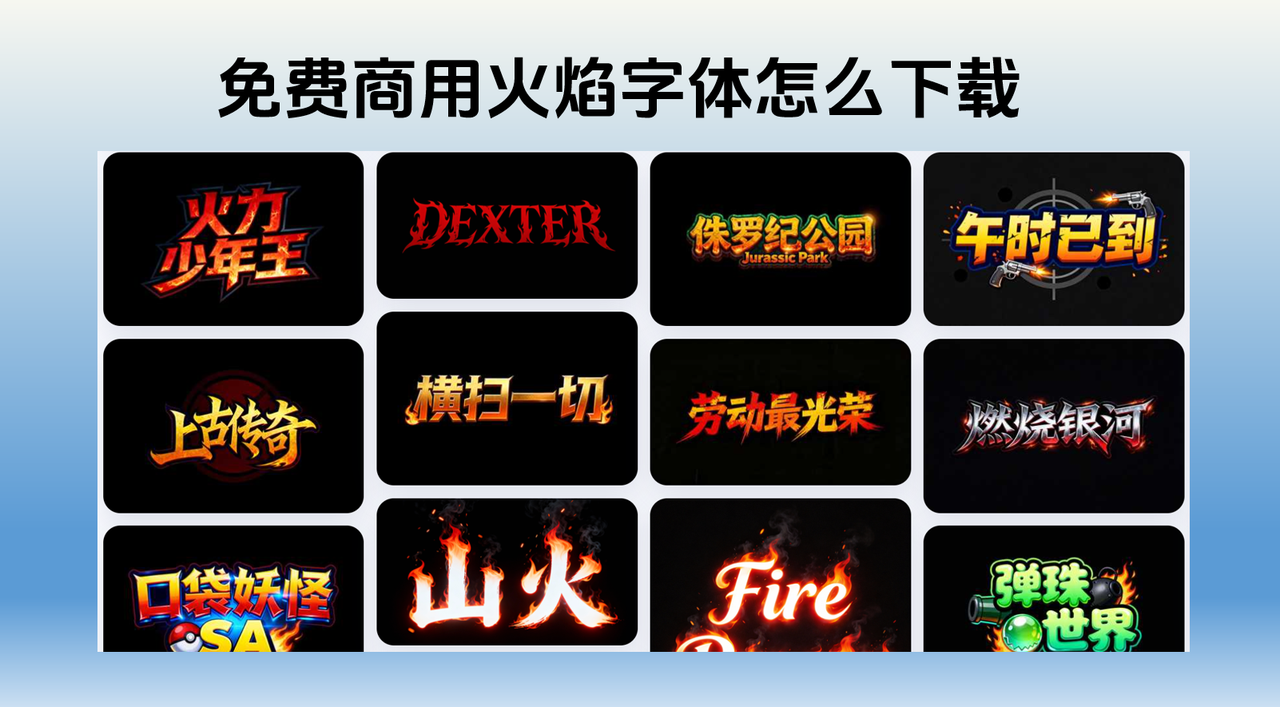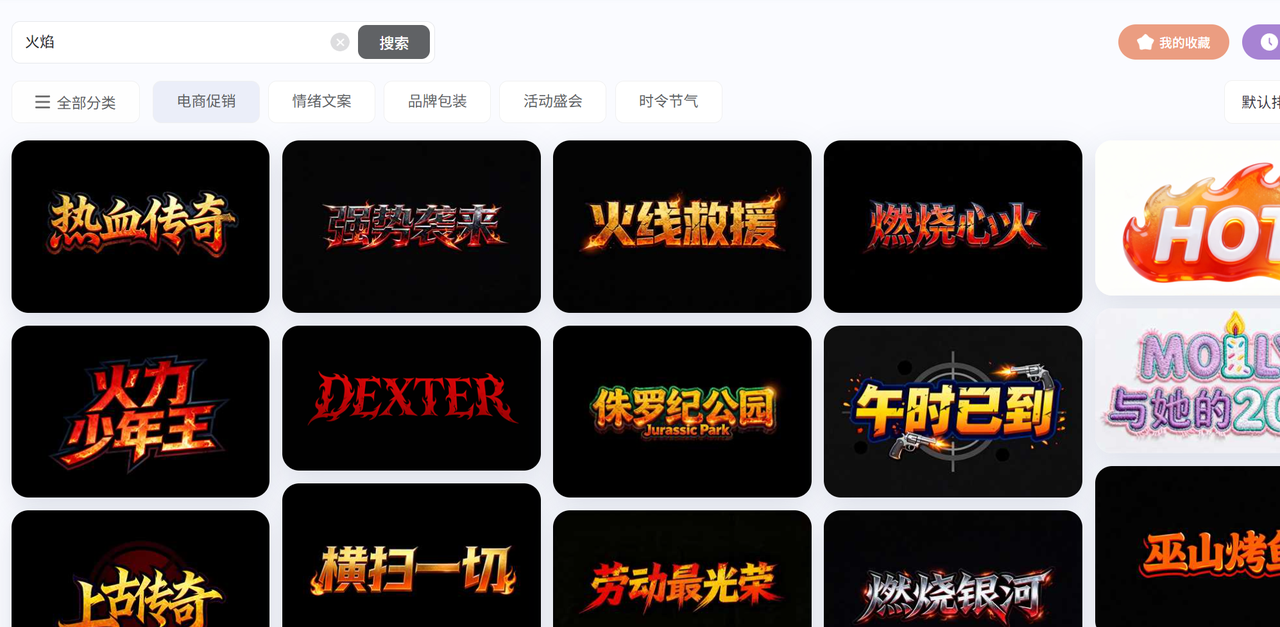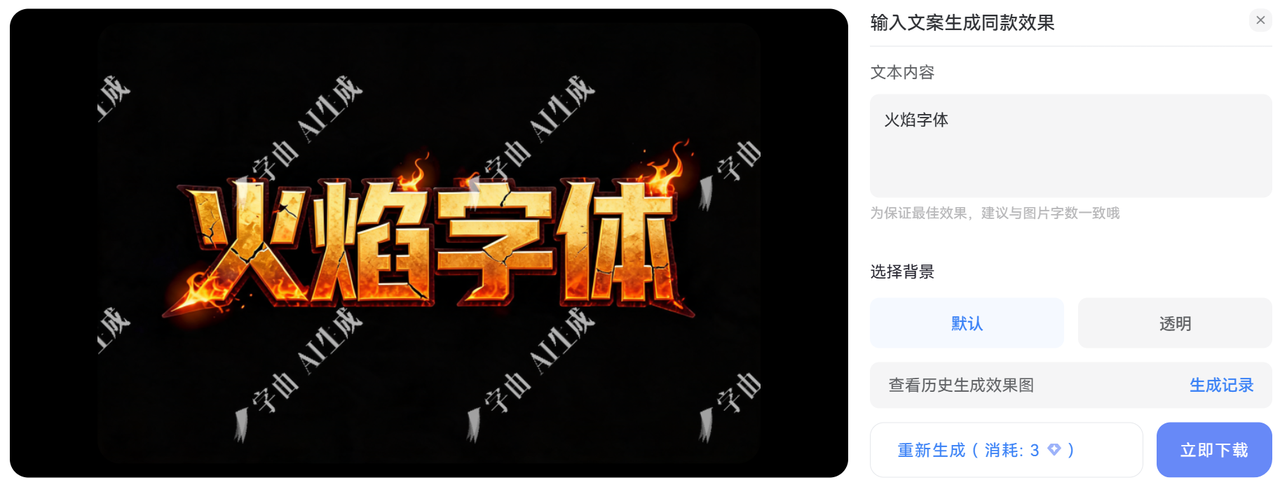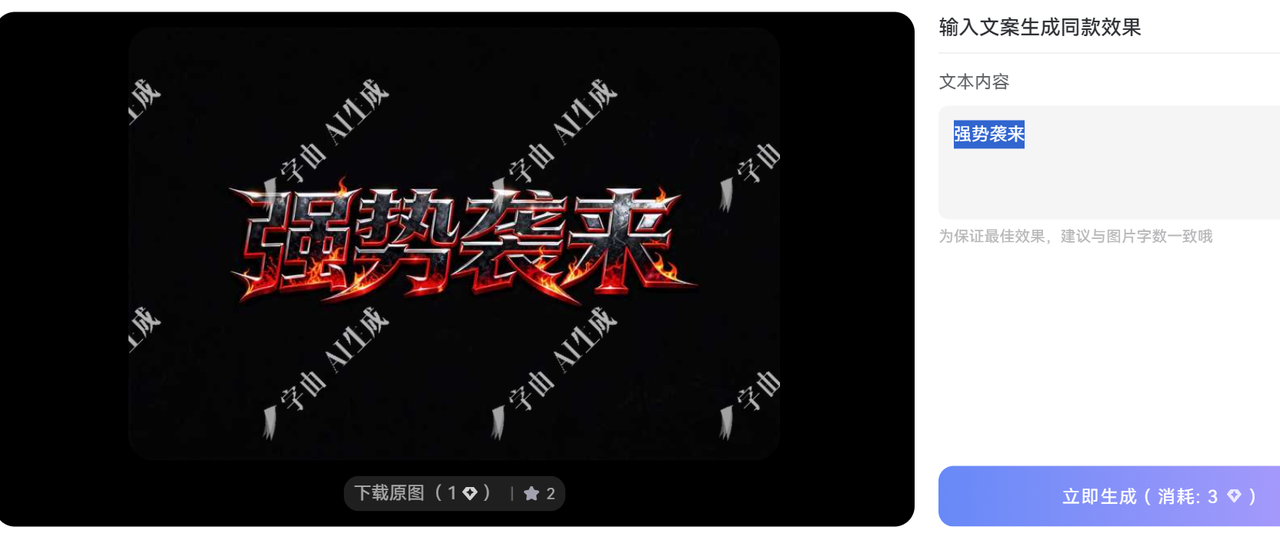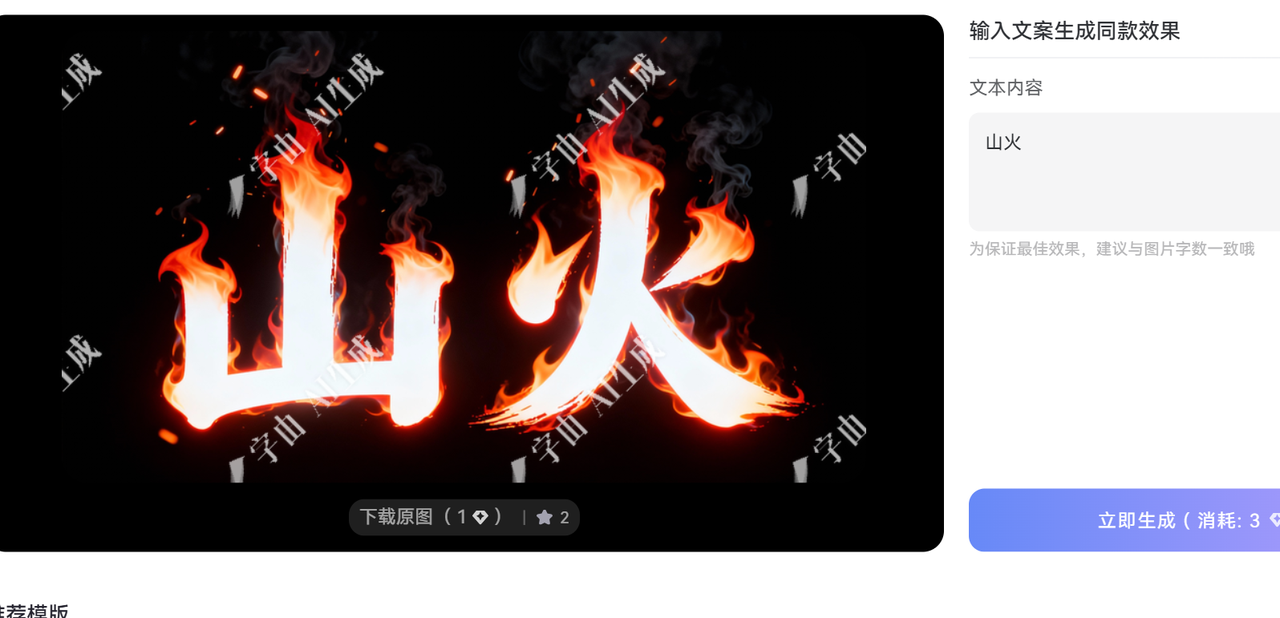
免费商用火焰字体怎么弄?教你用字由AI在线生成
做烧烤店老板要做招牌,要"火"一点;电竞活动要做主KV,要"燃"一点;暑期大促要做Banner,火焰字体这种强装饰的东西,比较难找,今天我告诉你一个思路,不一定非得找"字体文件",能直接生成可商用的火焰字效果图,其实更省事。我现在做火焰字、火光字基本都在这儿搞定,生成的图按平台规则可以直接商用,不用再纠结授权。
找火焰字体的弊端
自己画太慢。 PS里拿火焰笔刷一点点蹭,还要调图层模式、加外发光、做热浪扭曲,一个简单的"开业大吉"四个字能磨一下午。客户再来句"火再旺点""颜色偏橙一点",心态直接崩。
素材站的坑多。 很多标"免费火焰字体"的站,下载下来要么是.ttf但只支持英文数字,中文压根没有;要么是图片版,水印正好打在"火苗"最旺的位置,擦都擦不掉。
字由 AI 生成火焰字
字由本来大家熟悉的是通过字由客户端来下载和使用字体,但它现在做了个 AI 字体生成 的网页工具,不用装软件,浏览器打开就能用。
字体生成工具提供模板搜索功能,其它样式的字体,也可以通过搜索来快速查找
比如我输入“火焰字体”,需要注意进来输入的字体和模板中的字体保持一致
我比较推荐的几个火焰字体模板
强势袭来
游戏和动作电影宣传的场景比较适合使用
山火
看到这款不用多说,烧烤、烤肉非常的时候
几个小经验
字由AI字体生成出的是图,不是字体文件(.ttf/.otf 那种)。如果你需求是"要把火焰字体装进Word给老板写年终总结",那这个工具不对口,它对口的是海报/KV/招牌/电商图/Banner这类视觉场景。
火焰、霓虹、鎏金这类风格属于装饰字效,它家风格库是持续更新的,今天有"黏土""果冻""云雾""冰晶"这些,明天可能还会加新的火系细分。
最后
如果你也经常被"来点带火的字"这种需求支配,真的可以换个思路——别再满世界搜"免费商用火焰字体下载"然后赌授权了,去字由那个AI字体生成页面,几分钟就能完成火焰字体的生成。